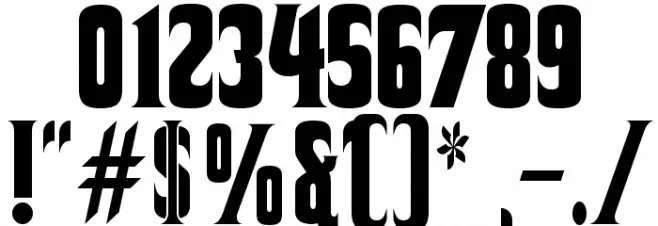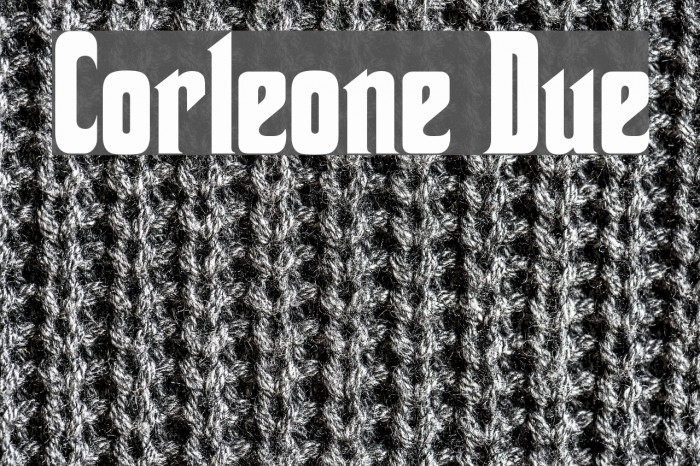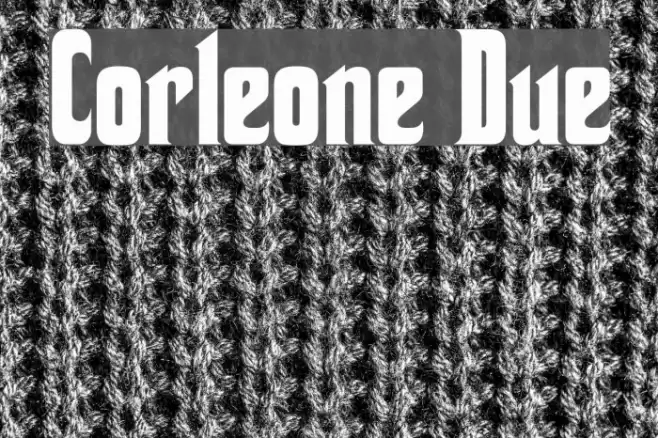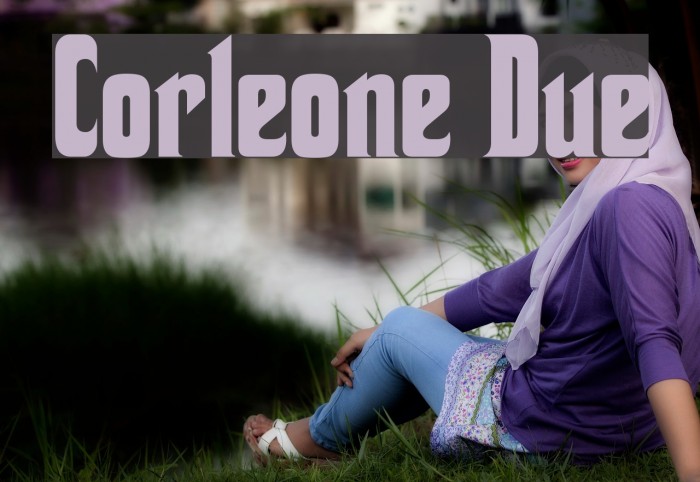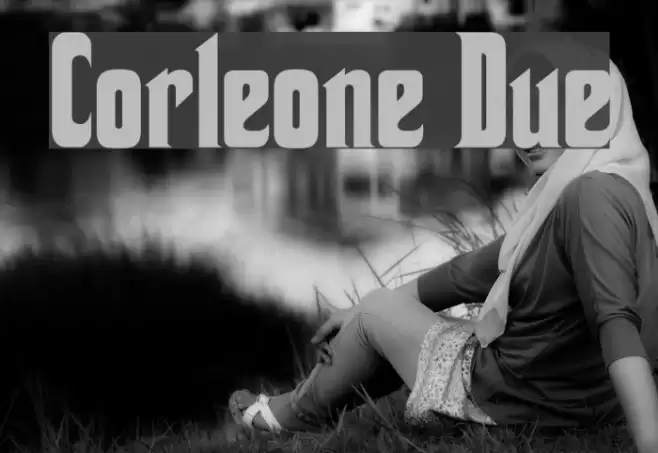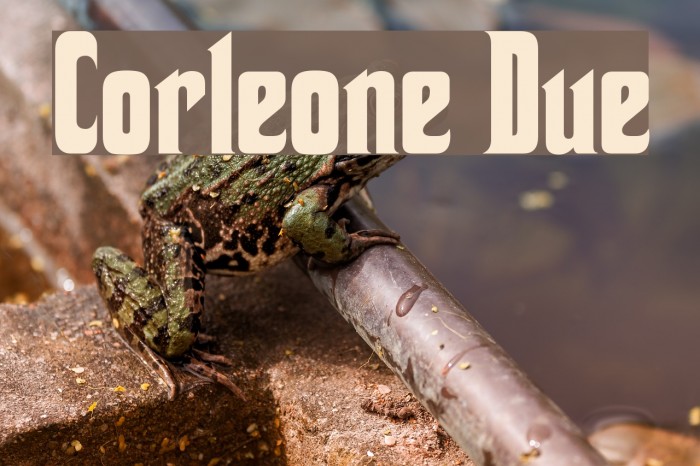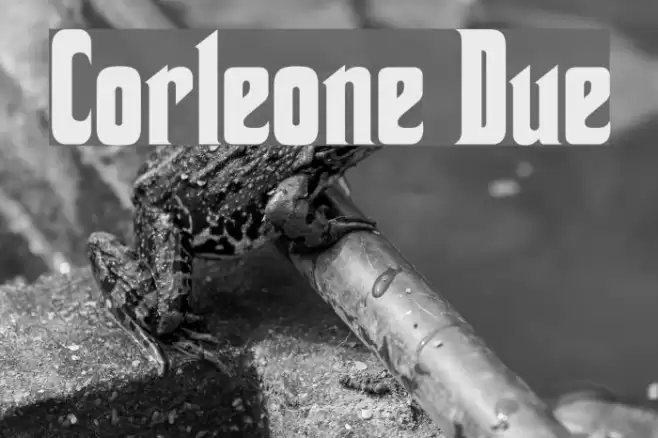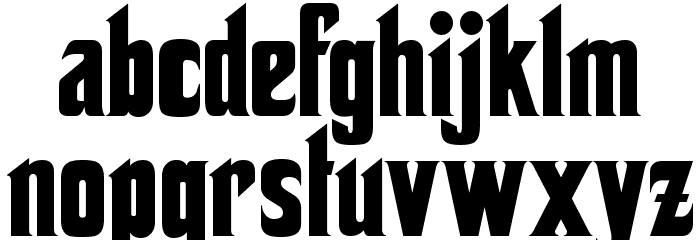
Corleone Due Font
| おすすめプロジェクト | Ideal for movie posters, vintage-themed designs, branding for bold products, and any project requiring a strong, impactful typeface. |